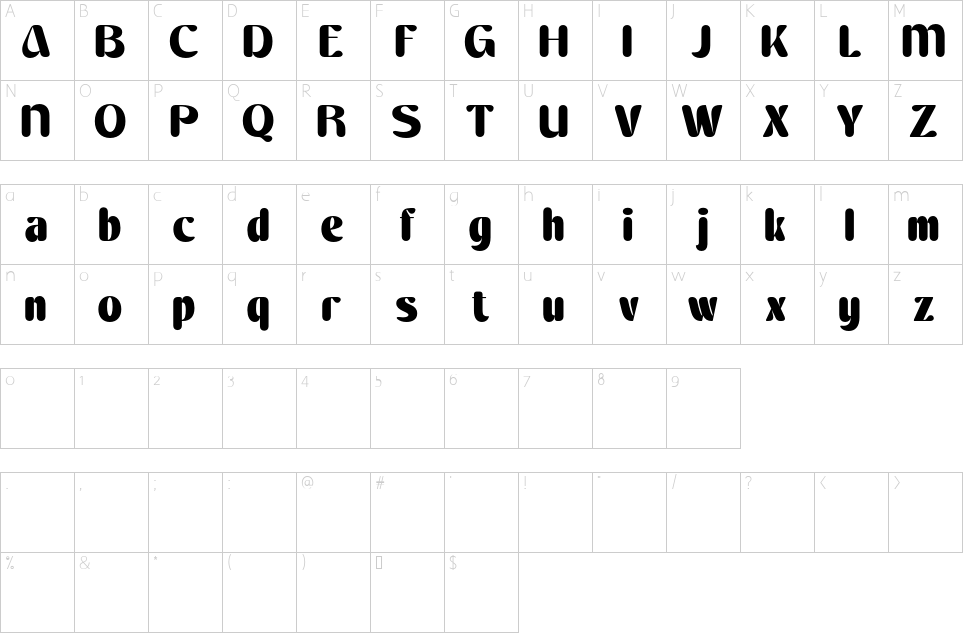
Descubra Arshine Rounded, uma fonte elegante e confortável projetada pelo Craft Supply Co. Arshine Rounded oferece um visual agradável e versátil, perfeito para design de layouts e gráficos digitais. Com seu design arredondado e suave, essa fonte traz um toque de simplicidade e sofisticação a qualquer projeto. Com o download gratuito disponível tanto para Windows quanto para Mac, Arshine Rounded é uma fonte que você pode experimentar imediatamente sem custos adicionais. Este design da Craft Supply Co já foi baixado 156 vezes, o que mostra sua popularidade entre designers e criadores de conteúdo. Não perca tempo, baixe sua cópia de Arshine Rounded hoje e inove seus projetos de design com uma fonte que combina elegância e facilidade de uso.